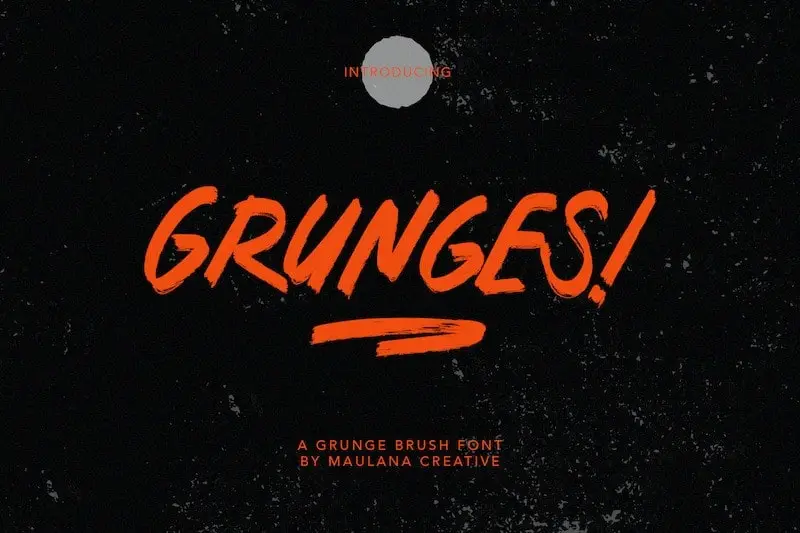
A fonte Grunges Brush é perfeita para estilos criativos que desejam dar um toque distintivo a suas criações digitais. Criada por Maulana Creative, essa fonte é especial porque apresenta caracteres maiúsculos e alternativas para letras minúsculas, além de incluir uma versão itálica extra. Suas características são perfeitamente adequadas para uma variedade de aplicativos gráficos, como assinaturas, cartões de boletim escolar, logotipos, citações em publicações, capa de revistas ou livros, cabeçalhos de websites, panfletos, roupas, marcações e embalagens. A sua personalidade única é perfeita para criar um estilo distintivo nas criações digitais. Seja você designer gráfico, ilustrador ou criador digital, a Grunges Brush certamente encaixa-se em seu portfólio de fontes favoritas.